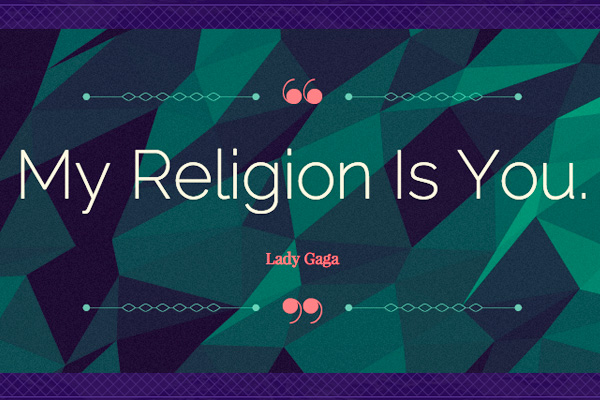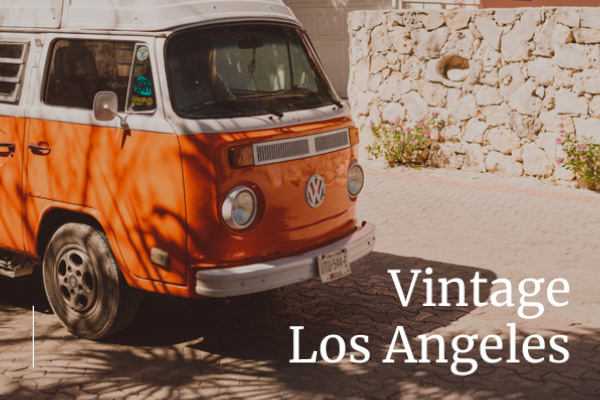
适合制作Logo的字体大全,新手必看这8款
6在制作Logo时,选择合适的字体至关重要。一个好的字体不仅能提升品牌辨识度,还能传达品牌的核心价值和个性。然而,面对海量的字体资源,很多人常常感到无从下手:到底哪些字体适合用来设计Logo?怎样挑选既美观又实用的字体?本文将结合我的实际使用经验,从多个风格和场景出发,帮你理清思路,推荐适合制作Logo的字体,并提供靠谱的下载渠道及免费字体获取方法,助你轻松打造高质量品牌标识。
现代简约风格的logo字体
现代简约风格的Logo通常注重线条简洁、形态规整,适合科技、互联网、时尚品牌。选择字体时,优先考虑无衬线字体(Sans Serif),这样更显现代感和专业性。
Montserrat
- 风格特点:圆润的几何无衬线字体,线条均匀,视觉冲击力强。
- 适用场景:科技公司、初创企业、电商平台、现代时尚品牌。
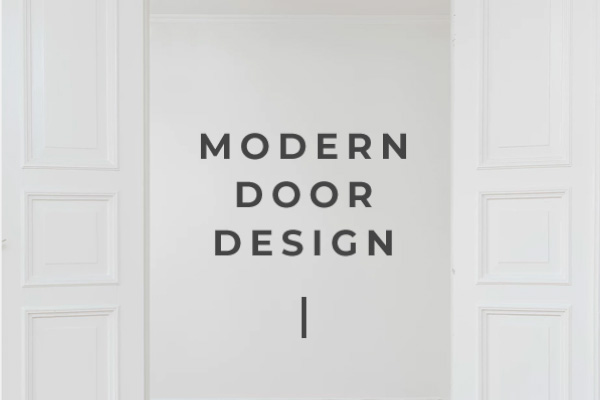
Raleway
- 风格特点:优雅的无衬线字体,整体轻盈通透,带有一定的现代感。
- 适用场景:设计工作室、创意品牌、生活方式类项目。
经典衬线风格的Logo字体
Merriweather
- 风格特点:清晰易读的衬线字体,带有一定的厚重感和稳健的线条。
- 适用场景:金融机构、出版物、教育品牌。
Playfair Display
- 风格特点:高对比度的衬线字体,优雅且具有复古韵味。
- 适用场景:高端品牌、奢侈品、时尚杂志。
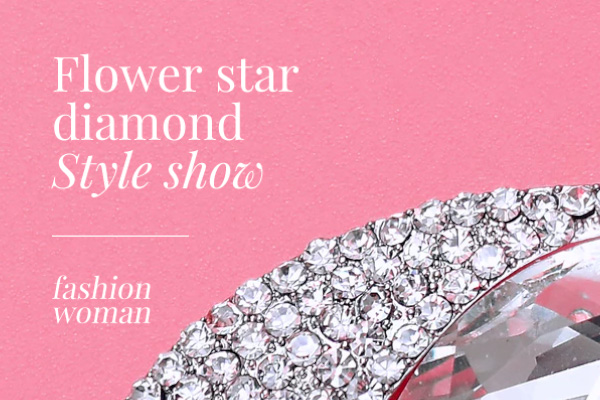
手写/书法风格Logo字体
Pacifico
- 风格特点:流畅的手写风格,带有复古风情,适合活泼甜美品牌。
- 适用场景:咖啡馆、手工艺品、儿童产品。
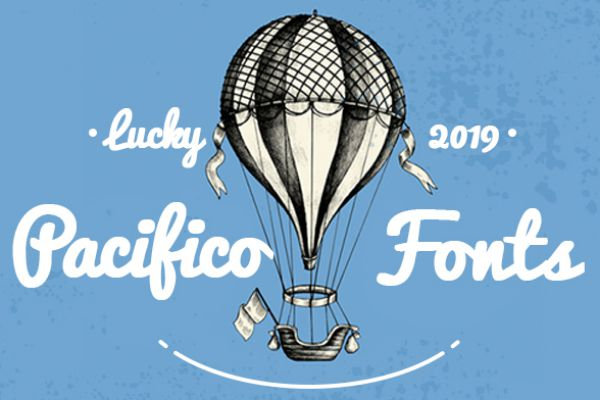
Great Vibes
- 风格特点:优雅的连笔书法字体,线条细腻柔和。
- 适用场景:婚礼品牌、时尚配饰、生活方式类产品。
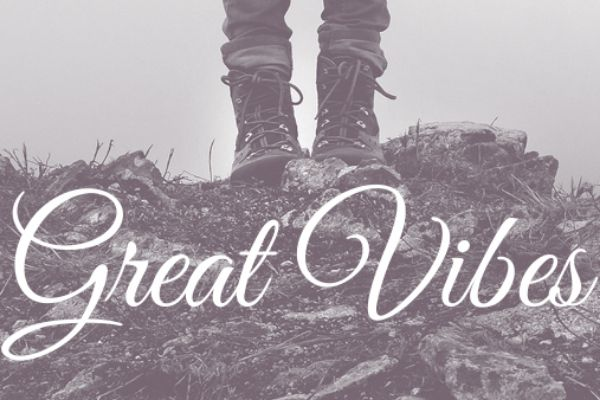
创意个性风格Logo字体
某些品牌希望通过Logo传递创新和突破传统的态度,此时更具设计感的装饰字体或手绘字体会非常合适。
Lobster
- 风格特点:饱满的手写风格,带有装饰性曲线,富有表现力。
- 适用场景:创意品牌、餐饮连锁、娱乐产业。
Bebas Neue
- 风格特点:粗犷的无衬线字体,极具冲击力,适合标题和标志设计。
- 适用场景:运动品牌、街头文化、广告标识。